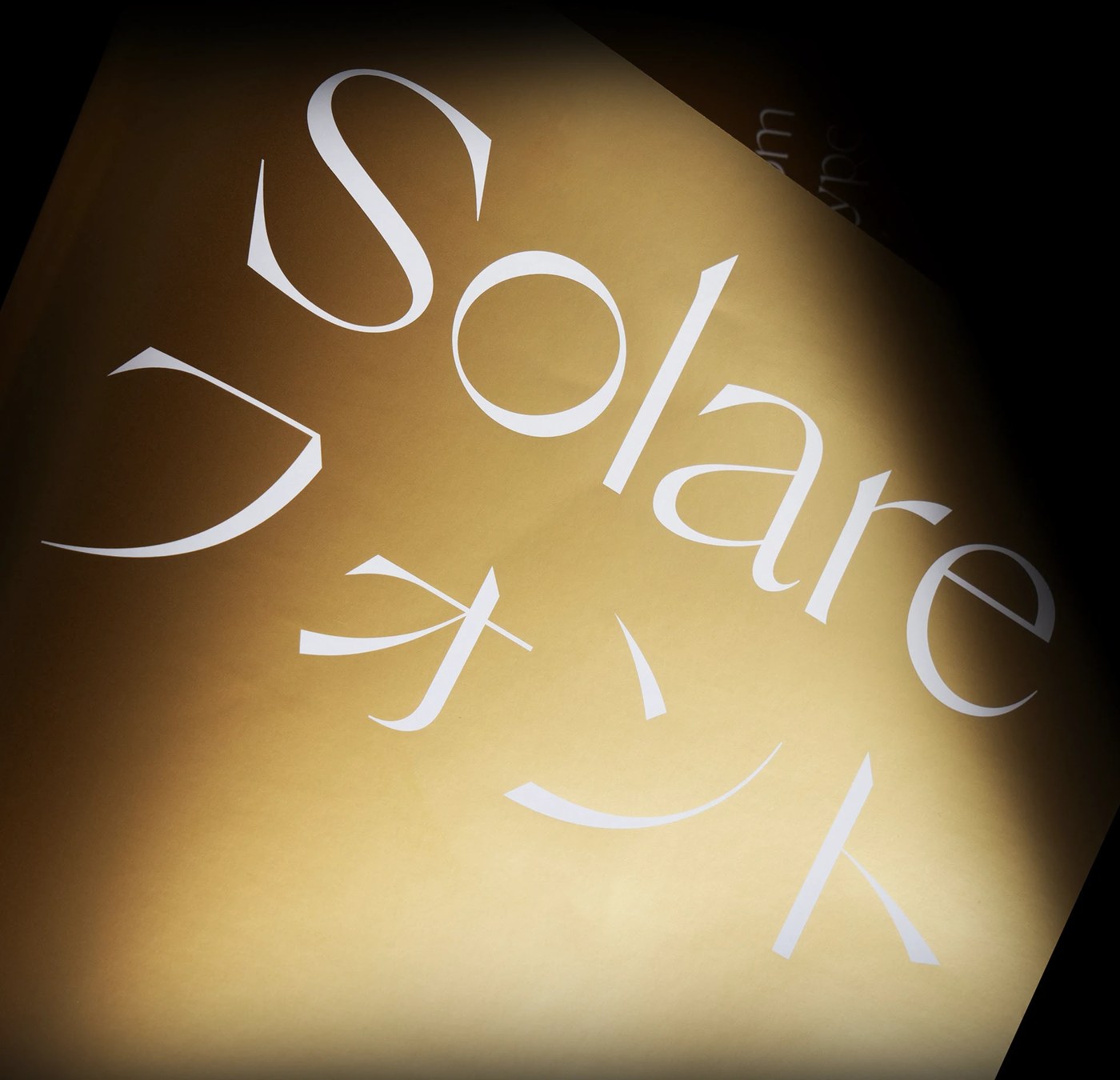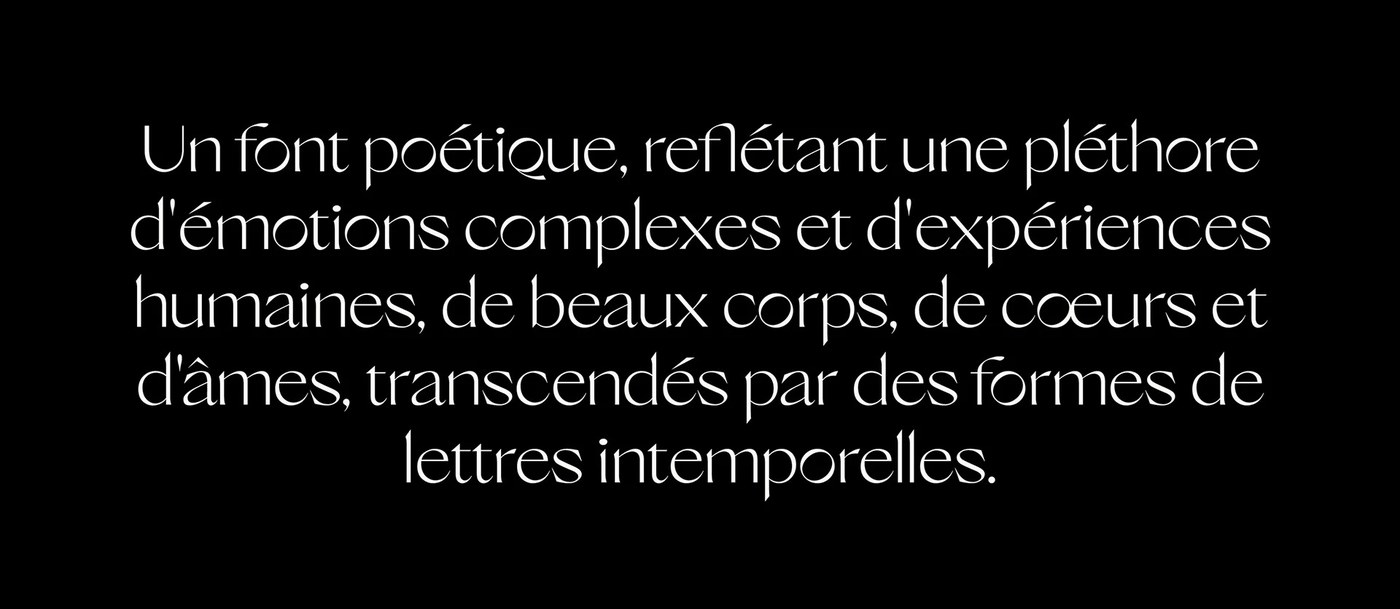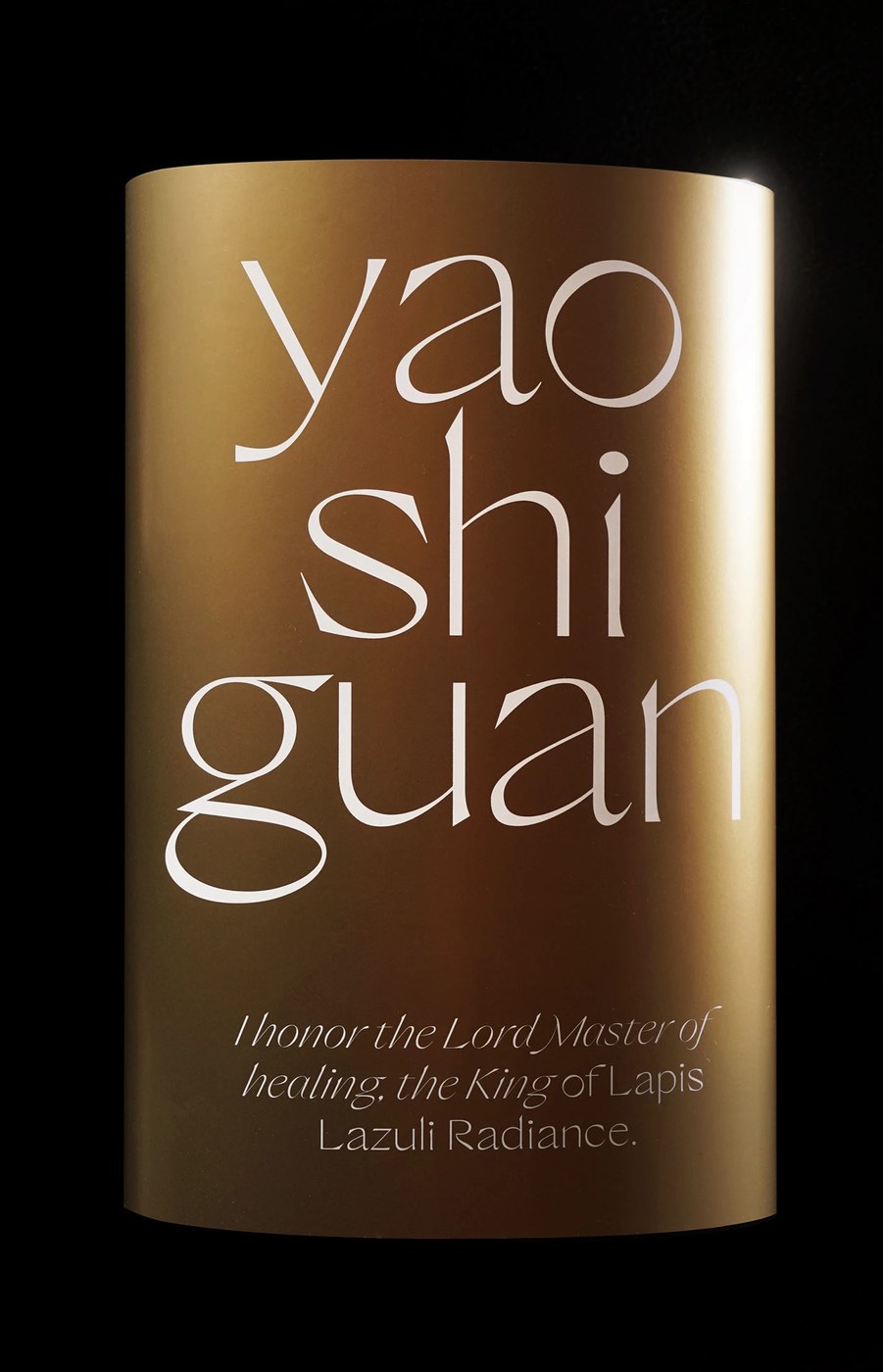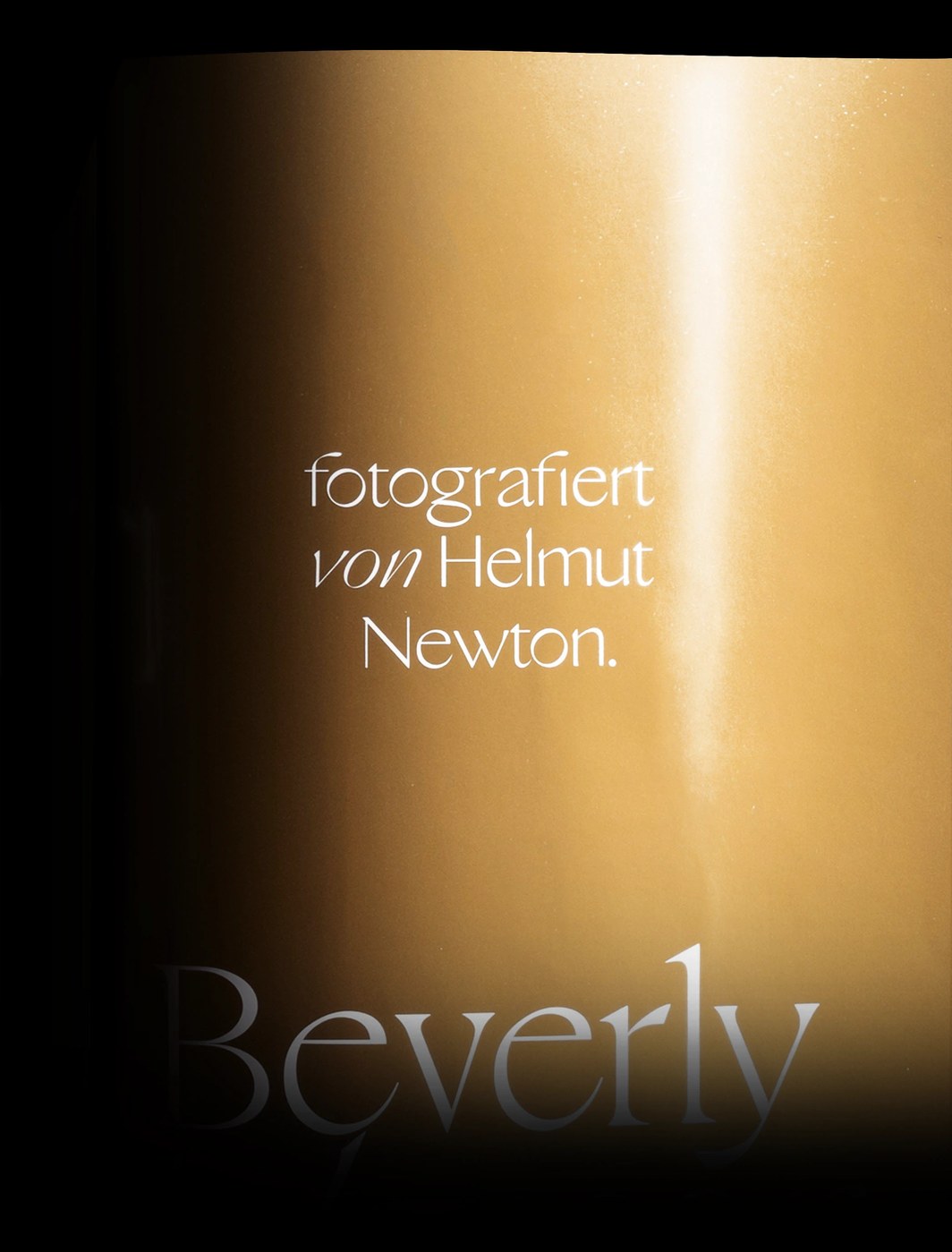
Solare là một dự án font chữ sans serif rất đáng chú ý từ Nikolas Wrobel của Nikolas Type. Sau 5 năm mài giũa, dự án đã thành công trong việc kết hợp nét tinh tế truyền thống cùng tính ứng dụng kỹ thuật số hiện đại. Bộ font sở hữu 16 style đa dạng từ nét fine đến black, đi kèm với các biến thể chữ nghiêng và những nét thay thế (alternates) độc đáo. Những yếu tố này mang lại sự ấm áp đầy cảm xúc cho cấu trúc kiểu chữ vốn dĩ đã rất gọn gàng, tạo thành một công cụ cực kỳ hữu ích cho các layout thiết kế ngày nay.
Thiết kế của Solare là sự cân bằng giữa hình khối grotesque cứng cáp cùng những chi tiết serif mềm mại. Các letterform có độ tương phản cao ở các điểm đầu cuối (terminals) cùng góc cạnh sắc nét, tạo nên sức hút thị giác vô cùng thú vị. Khi sử dụng, bộ font duy trì được nhịp điệu thị giác cân đối, hệ thống lưới modular giúp định hình bố cục và để lại nhiều khoảng không (negative space) thoáng đãng. Mọi đường nét đều được căn chỉnh tỉ mỉ trên baseline. Sự tiết chế về mặt hình học tạo nên độ rõ ràng, khiến font chữ này hoàn hảo cho cả các tiêu đề lớn lẫn các đoạn văn bản dày đặc.
Khai thác sự linh hoạt của font sans serif
Nhờ vào trục font biến đổi (variable font axis), Solare thích ứng cực tốt với nhiều độ dày khác nhau. Sự thay đổi này đảm bảo font luôn hiển thị sắc nét trên màn hình kỹ thuật số. Trong các bản in thực tế, chữ cái hiện lên ấn tượng trên các vật thể vàng kim hình trụ, với ánh đèn làm nổi bật sự tương phản xúc giác của mực in trắng trên nền giấy có vân. Bên cạnh đó, các chữ cái bằng thủy tinh và các tác phẩm điêu khắc từ Jon Vio mang đến những phản chiếu ba chiều, giúp biến những đường cong kỹ thuật số thành các hình khối thủy tinh thực tế. Sự tương tác giữa các chất liệu này tạo nên trải nghiệm thị giác đầy ấn tượng.
Nikolas Type đã khẳng định được vị thế của mình khi kết hợp các truyền thống in ấn cổ điển với khả năng của phần mềm hiện đại. Font chữ này chứng minh rằng tính tiện dụng và khả năng biểu đạt cảm xúc hoàn toàn có thể song hành. Với bộ ký tự hỗ trợ đa ngôn ngữ, bao gồm cả tiếng Nhật, Solare là sự lựa chọn linh hoạt cho các dự án branding toàn cầu cũng như các ấn phẩm biên tập. Dự án này cho thấy cách một font chữ có thể vừa mang cảm giác ấm áp, vừa đảm bảo tính kỷ luật trong thiết kế.
Các hệ thống font chữ ngày nay cần phải vận hành tốt trên nhiều phương tiện khác nhau. Solare đáp ứng yêu cầu đó một cách tinh tế, cung cấp cả khả năng kiểm soát kỹ thuật lẫn sự rung cảm về mặt cảm xúc. Designer có thể thoải mái thử nghiệm với trục biến đổi để tạo ra độ dày riêng biệt, giúp các studio xây dựng bản sắc độc đáo. Đây thực sự là một nghiên cứu đầy kỷ luật về thiết kế chữ và đặt ra tiêu chuẩn cao cho các xưởng thiết kế font độc lập hiện đại.